Bras
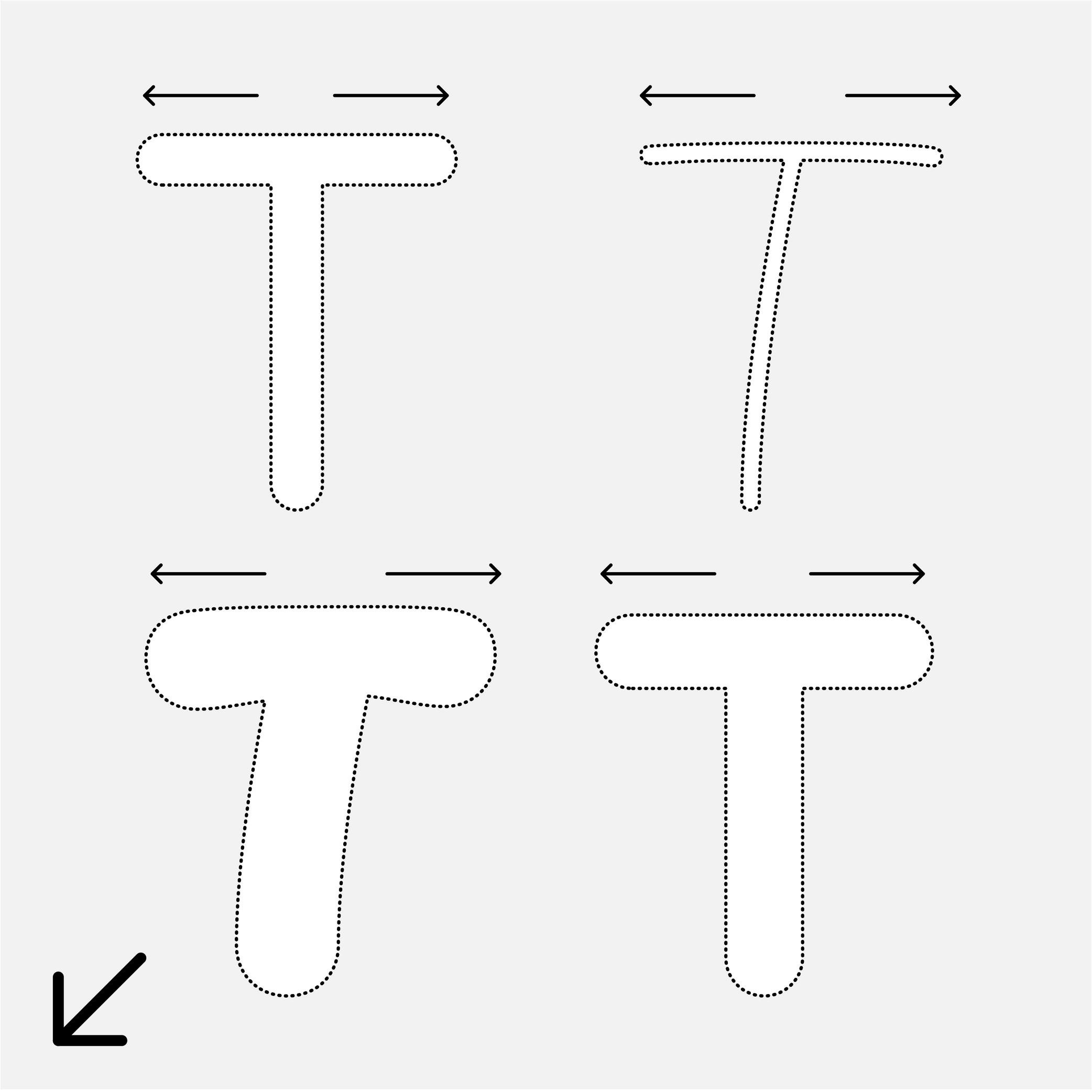
Pour désigner et décrire les parties d’une lettre ou d’un quelconque caractère, on emprunte de nombreux termes issus du vocabulaire architectural, de l’anatomie humaine ou animale. On parle d’ailleurs d’anatomie de dessin de caractères.
Pour l’alphabet latin, le bras est la barre horizontale en haut de la lettre T ou celle à mi-hauteur du E et F.